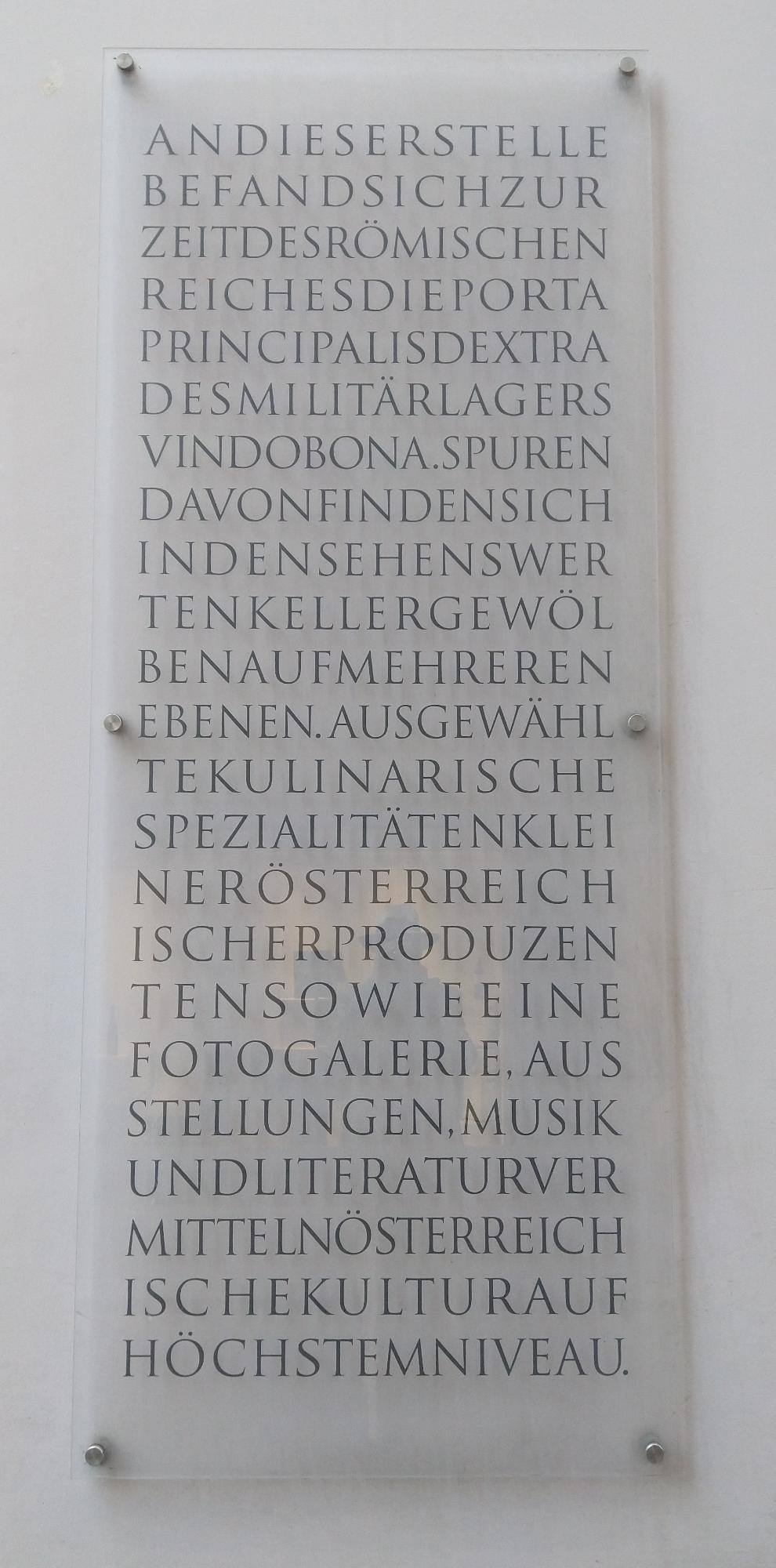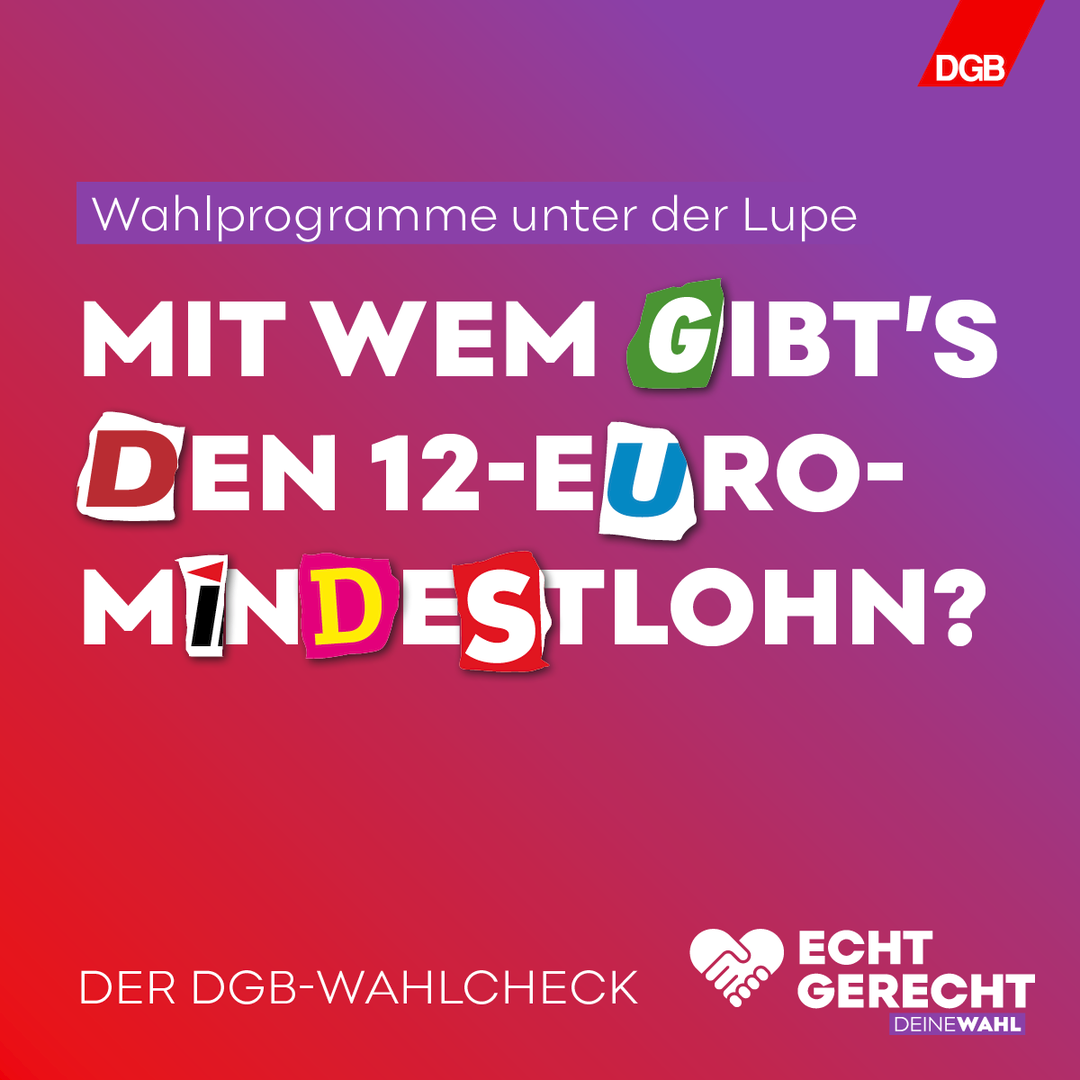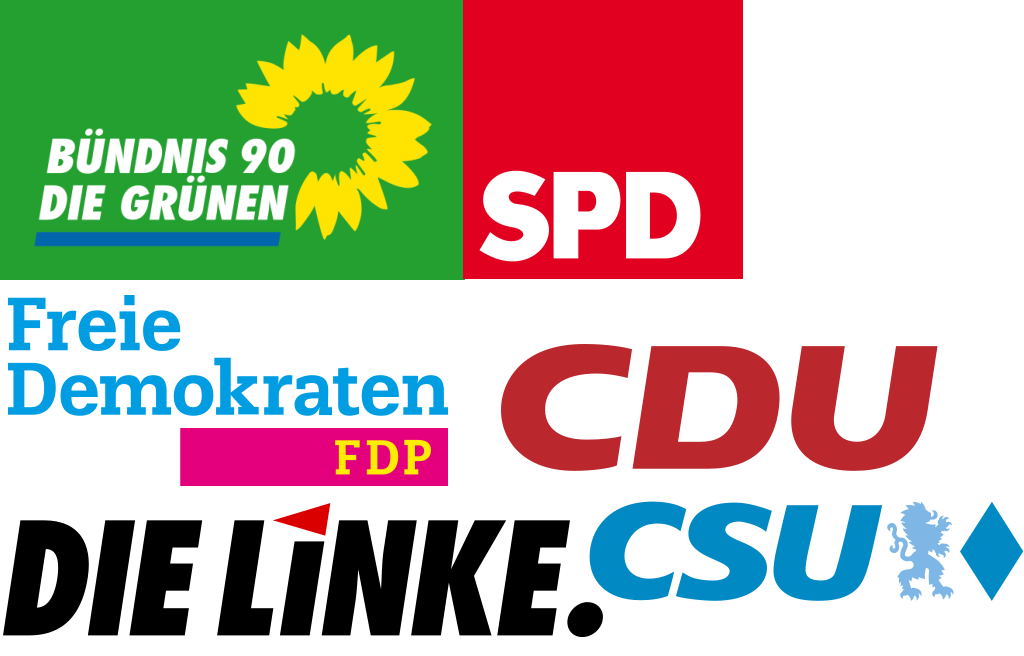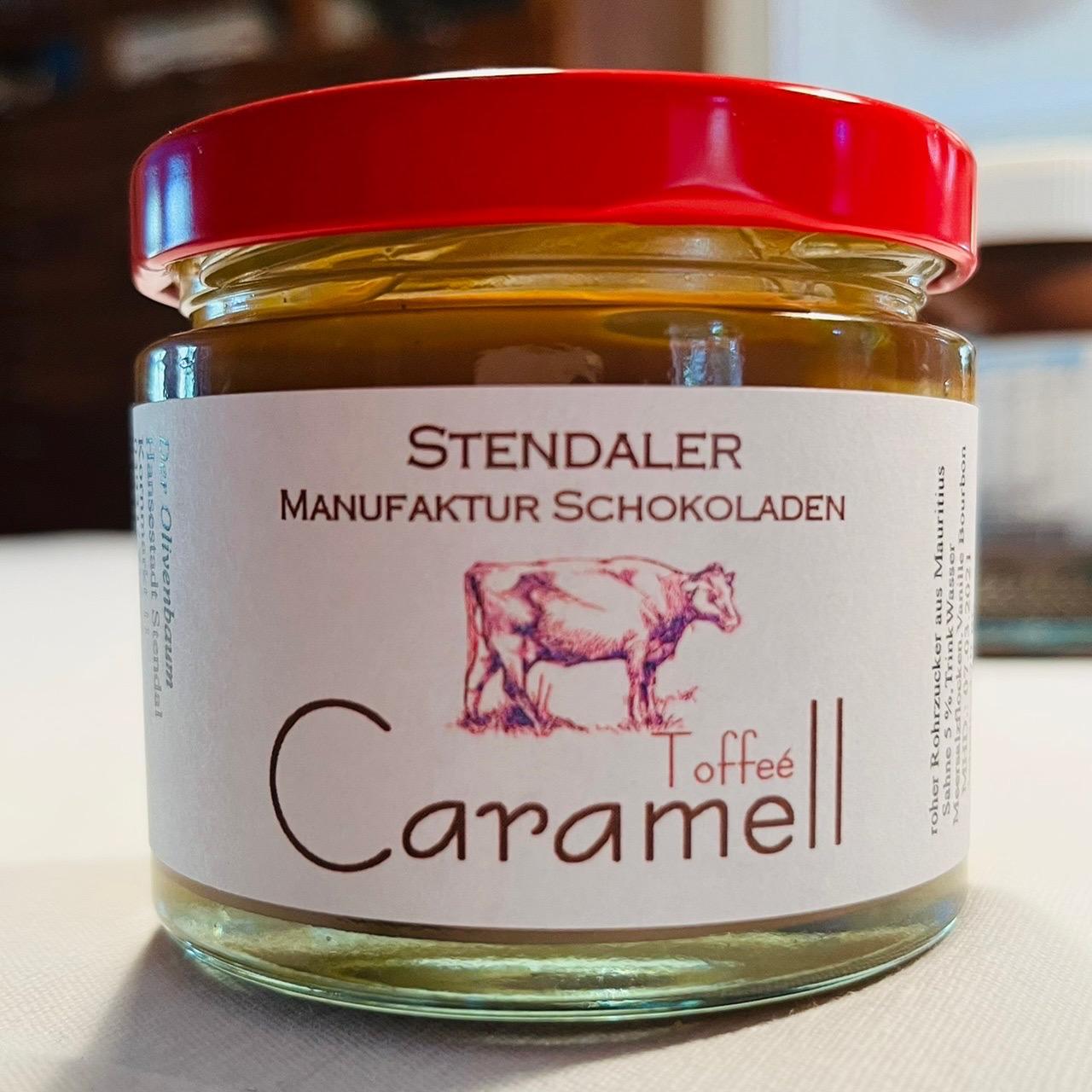
Ich habe versucht, aus den Schnipseln ein Wort zu bilden. Das ergab aber alles keinen Sinn. Dank R::berts Erklärung brauch ich nicht weiter zu scrabbeln. Danke!
Da fordern in diesem Punkt wohl alle das Gleiche?
Leider nein. Die Parteien-Vergleiche sind aber sehr interessant beim DGB. Aber, wie sollte es anders sein, reichlich linksgrün versifft :-D Diese Banner, es ist nur ein Teil, ich wollte ja nicht mein Anhangkontigent komplett zuballern, hab ich übrigens bei dgb.de nicht gefunden, die scheinen dem Social Media-Team vorbehalten zu sein, zum Beispiel bei https://www.facebook.com/DGB.Gewerkschaftsbund (da hab ich es zumindest her).
Aber ich vergaß unsere mitlesenden Ausländer, deswegen noch einmal die Parteilogos lieblos zusammengestümpert von mir (Quelle: s.v. wikipdia.de) und ein ganzes Banner vom dgb (Quelle s.o.)
Ich kapier's nicht 😞
Die Buchstaben sind auf den verschiedenen Parteilogos ausgeschnitten. Hier eine Übersicht:
Die Auflösung im Einzelnen:
GRÜNE
CDU
CSU (echt  bayrisch in blau-weiß)
FDP (in den grauenhaften Farben der neuen CI)
Die Linke (man sieht auch noch einen Fetzen den Winkels über dem i)
SPD (in der altbewährten Futura)
Waren die bayrischen Farben nicht Weiß-Blau? 😄
Jaja, ich weiß, die Bayern sind ständig blau? Bzgl. der Reihenfolge hast Du recht ... Ich kenne die Reihenfolge aus anderen Zusammenhängen idR umgekehrt.
Auch wenn ich eher Braun-Weiß bin, würde ich jenen Farben auf jeden Fall noch Schwarz hinzufügen 🙂
Leerzeichen sind überschätzt.
Ich denke, dass man die Tafel ganz im Sinne römischer Inschriften angelegt hat – also ohne Leerzeichen und Silbentrennung. Das passt also schon, wenngleich es sehr ungewöhnlich anmutet. Dennoch ist die Umsetzung miserabel.
Da hast Du definitiv Recht, wobei die Römer durchaus Zeichen (Beispiel 1, Beispiel 2, Beispiel 3) kannten, um Wörter gegeneinander abzugrenzen. Da hätte werauchimmer sich durchaus von inspirieren lassen können.
Ich hatte leider keine Zeit mehr, andere (alte) Inschriften dieser Art in Wien zu dokumentieren. Davon gibt es in Wien einige (StefanB liegt hier mit seiner Vermutung goldrichtig), diese sind, obwohl genauso gedrängt gemeißelt, viel besser lesbar, als diese Inschrift. Hier hatte man doch alle technischen Möglichkeiten eines Satzprogrammes und hat sie nicht genutzt.
Tatsächlich kann so etwas auch als große Kunst verkauft werden, ich hatte mich hier ja auch schon mal über das CD der Alsterdorfer Anstalten beklagt, da ich es extrem unruhig bis zur Unleserlichkeit finde. Da hatte jemand mich hier informiert, dass das ein preisgekröntes Design (die Website der Agentur gefällt mir übrigens genauso wenig) ist. Manchmal muss man Kunst einfach Kunst sein lassen 😉
Kleiner Merksatz dazu: «Blau-weiß» sagt der Preiß', «weiß-blau» stimmt genau.
Siehe auch die Bayernhymne, dort stehts im Refrain.
Tu ich eigentlich nur, wenn ich Bayern ärgern will 🙂